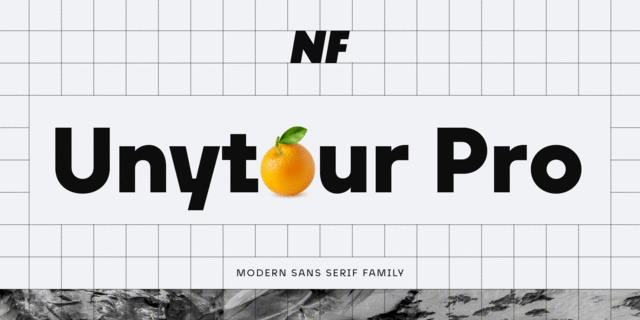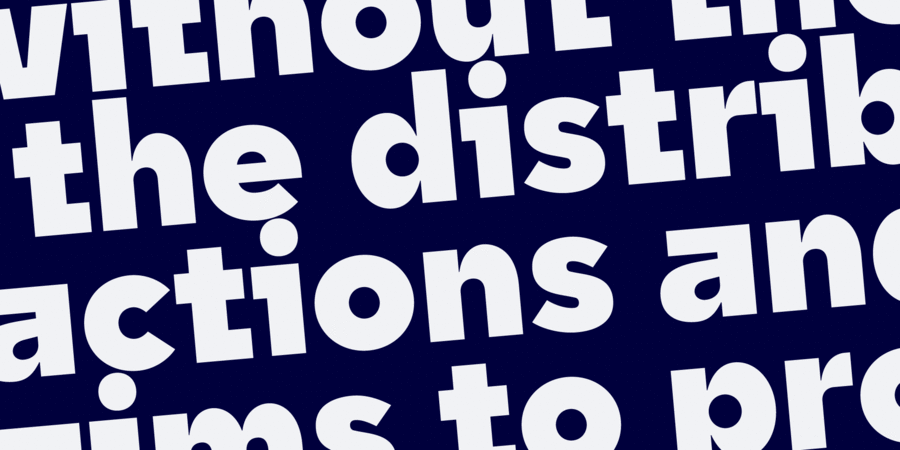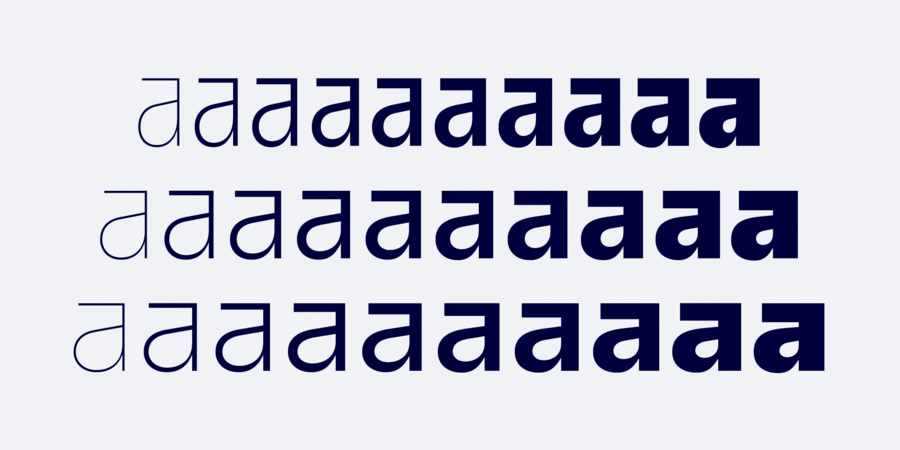
Опис гарнітури Unytour Display Pro – це сучасний шрифт без зарубок, що складається з 60 шрифтів. Він має 10 товщин, від Thin до Heavy, а також курсив для кожної товщини у трьох ширинах. Кожна товщина включає 1000 гліфів, альтернативні символи (такі як A, G, I, R, a, l, t, y, Л, б, и, м, ф, у) та функції OpenType. Unytour Display Pro відзначається високою читабельністю як у друкованих, так і в цифрових застосунках, зокрема на екранах телевізорів та інших пристроях. Шрифт розробив Микола Савчук у 2024 році.
Особливості сімейства шрифтів Unytour Display ProХіт десятиліття:
Асоціації з сімейством шрифтів Unytour Display ProОсобистість і характер гарнітури:
ламаний, кутастий, точний, рівний, прямокутний, статичний, логічний, стійкий, автоматичний, штучний, холодний, інженерний, міський, різкий, чіткий, креслярський, чистий, сучасний, гострий, тонкий, дротяний, скляний, легкий, прохолодний, ясний, невагомий, прозорий, крихкий, модний, худий, оригінальний, дивний, твердий, надійний, впевнений, сталевий, машинний, урбаністичний, крижаний, квадратний, експериментальний, дзвінкий, сміливий, рубаний, характерний, незвичайний, цікавий, серйозний, переконливий, залізний, мужній, тоталітарний, стабільний, гучний, сильний, кондовий, політичний, революційний, індустріальний, техногенний, військовий, армійський, солдатський, грубий, робочий, мотивуючий, залізничний, амбітний, жорсткий, брутальний, ігровий, міцний, важкий, авторитетний, значний, важливий, монументальний, суворий, крутий, кричущий
креслення, дизайн, туалетна вода, мода, небо, конструктор, архітектура, урбаністика, коворкінг, Місто, інтер'єр, гра, анімація, електроніка, війна, армія, зброя, машинобудування, мітинг, політика, шахта, завод, металургія, верстат, інструмент, будівництво, будматеріали, тара, склад, порт, ящик, патрони, техніка, промисловість, електростанція, енергетика, ремонт, депо, шахтар, шолом, уніформа, вагон, авіація, літак, страйкбол, взуття, залізниця, робочий, страйк, Протест, кубики, лего, танк, тренажери, революція, блокбастер, бойовик, екшен, цегла, вантажівка, далекобійник, мотор, двигун, реп, концерт, селфі, головокрутка Гарнітура асоціюється з віком: